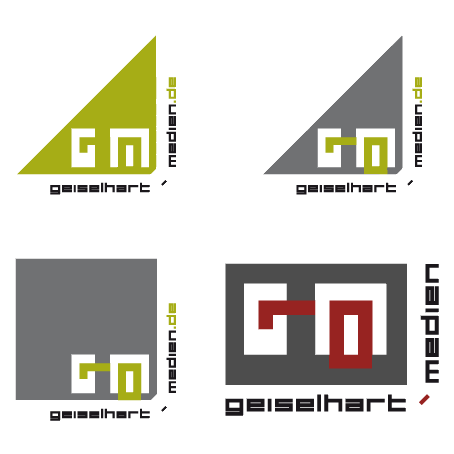
Eure Meinung zum neuen Logo
Hallo allerseits!
Habe heute folgende Logo-Varianten entworfen und möchte nun gerne Eure Meinung dazu hören.
Bei der Firma handelt es sich um ein Büro für digitale Medien.
Was mir bereits aufgefallen ist, dass die umlaufende Schrift ein wenig "zu läuft" und daher bei kleiner Darstellung schwer zu lesen ist - welche Schrift wäre passender? ...
Hätte ich nicht gewusst, welche Buchstaben das sein sollen, hätte ich in drei von vier Fällen nicht erkannt, dass es sich um ein G und ein M handelt.
Das würde ich an deiner Stelle deutlicher herausarbeiten.
Puh, was ist denn das? :? Das sieht richtig schlimm aus und die Schrift ist auch groß nicht gerade als besonders lesbar zu bezeichnen. Sähe ich solch Logo, würde ich um diese Firma, wenn es um Design geht, einen großen Bogen machen. Klingt hart, ist es auch.
1. Man darf nie mehr als eine gestalterische Idee in ein Logo packen.
2. Diese muß sich auf den ersten Blick erschließen.
3. Ein Logo wird nur wahrgenommen, wenn das Auge Halt findet und nicht ständig zwischen einzelnen Gestaltungselementen hin- und herirren muß
4. Daraus folgt: Weniger ist mehr.
5. Noch weniger ist noch besser.
6. Wenn es schon ganz wenig ist, überlegen, was man noch weglassen könnte.
7. Dann ist es an der Zeit, das ganze zu überarbeiten, um es erheblich zu reduzieren.
8. Zum Schluß noch vereinfachen.
9. Das Deutsche Bank-Logo danebenlegen. Wenn der eigene Entwurf immer noch komplexer ist, überlegen, was man noch weglassen könnte.
10. Das Logo mal spaßenshalber mal an sich selbst faxen und sehen, was davon übrigbleibt (Einfarbversion in geringer Auflösung muß funktionieren).
Weder noch. Digitale Medien --> das Ding wird am Bildschirm angezeigt werden --> das muss am Schirm zu 100% klappen, nicht "etwas besser als die andere Variante" sein "aber auch noch nicht so richtig."
Und so hart es klingt (und ich hoffe du bist mir nicht böse): die anderen haben schon recht, das ist kein Logo, noch nicht mal im Ansatz, sondern ein ideenloser Haufen der zu keinem Ganzen wird.
Ui, Ui, Ui, ich sag nur eins "Weniger ist mehr", das habe ich mir ganz GROSS auf die Fahne geschrieben.
... Je einfacher du das Logo gestaltest desto besser erkennbar. Und der Schriftzug ums Eck ... Sorry das geht gar nicht!
Sag lieber gluecklicherweise haben wir nie ausgelernt :D
Stellt sich aber trotzdem die Frage, warum die Amis besser sind.
Liegt es an der Ausbildung? Liegt es an mehr Freiheit fuer den der gestaltet? An der anderen Auffassung von Gestaltung auch auf Kundenseite?
Und braucht's fuer den unverkrampften Umgang mit Gestaltung nur unverkrampfte Gestalter oder auch unverkrampfte Kunden und Zulieferer?
I beg to differ.
Will sagen: Gestaltung ist nicht messbar und ich habe schon unglaubliche visuelle Verbrechen jenseits des großen Teiches gesehen. Davon abgesehen kommt es durchaus vor, dass Europäer für amerikanische Unternehmen gestalten und umgekehrt.